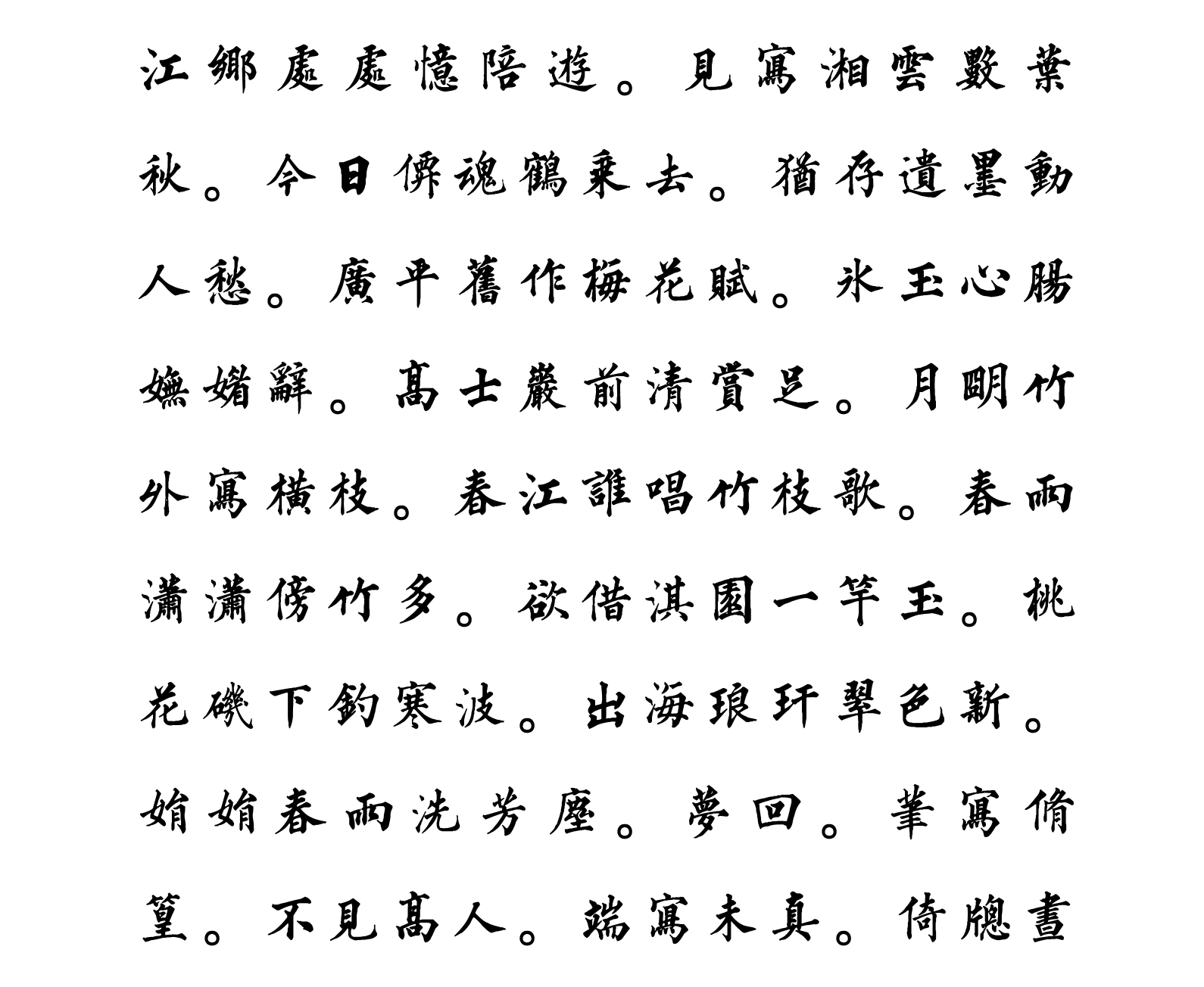
关于汉标成亲王法书册 字体字库信息
字体全名: 汉标成亲王法书册
字体简介: 1、下载须知:汉标成亲王法书册字库非标准GB2312字库。本字库只包含了真迹书法原稿中的部分字体。字库中字数的多少取决于原稿的字数的多少。你可以通过该字详情页上面的输入框如果有明白的请先联系字觅客服咨询。 2、简介:本字库由“汉标字库”根据收集到的真迹书法图片,并运用抠图、处理背景图、运用造字软件书法作品调整字体笔画基本位置,合理布局,提高清晰度,去除笔画边缘毛刺及脏点,纠正错别字,均衡整体文字的大小,再次创作而制作成现代字库,再将原版汉字逐字编码代入模板,在制作成小字库。这样做有助于中国古代书法艺术的传承具有划时代意义,并且通过把古代名家书法真迹制作成现代字库,让更多书法爱好者能够通过电脑打字使用,真正感受到古代名家书法之美。并且也可以在各种场景下应用。 3、古代真迹的书法家有:王羲之、王献之、欧阳询、颜真卿、柳公权、赵孟頫、苏轼、黄庭坚、米芾、蔡襄等